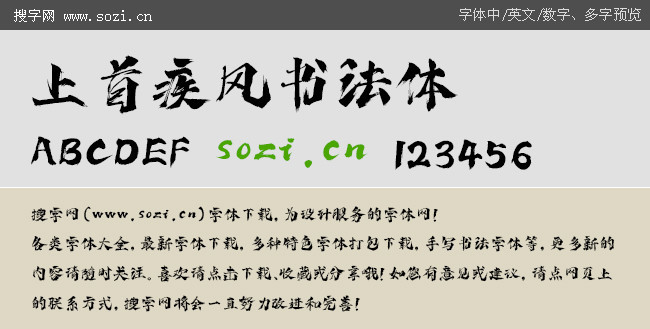
上首疾風(fēng)書(shū)法體
搜字網(wǎng)給大家提供一款上首疾風(fēng)書(shū)法體中文字體下載,上首疾風(fēng)體,字體風(fēng)格銳利,鈍點(diǎn)強(qiáng)力,夸張的筆鋒增添了字體的活躍性,而且字體中粗細(xì)銜接,使字體顯得生動(dòng)。適用于搭配標(biāo)志、廣告標(biāo)語(yǔ)、商業(yè)廣告等高端屬性。